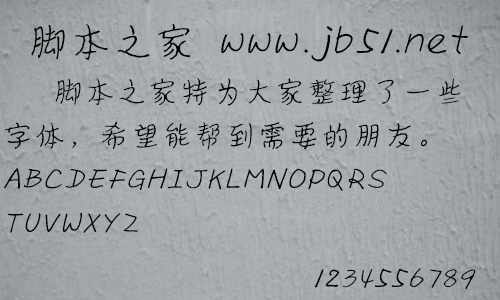
小豆島瀨戶風(fēng)車(chē)簡(jiǎn)體字體是由銳字工房出品的手寫(xiě)藝術(shù)字體,這款字體的筆觸較為纖細(xì),字體書(shū)寫(xiě)灑脫,排版整齊,具有很好的視覺(jué)感,適合應(yīng)用于藝術(shù)設(shè)計(jì)、平面宣傳設(shè)計(jì)、網(wǎng)頁(yè)設(shè)計(jì),書(shū)法字帖等領(lǐng)域。